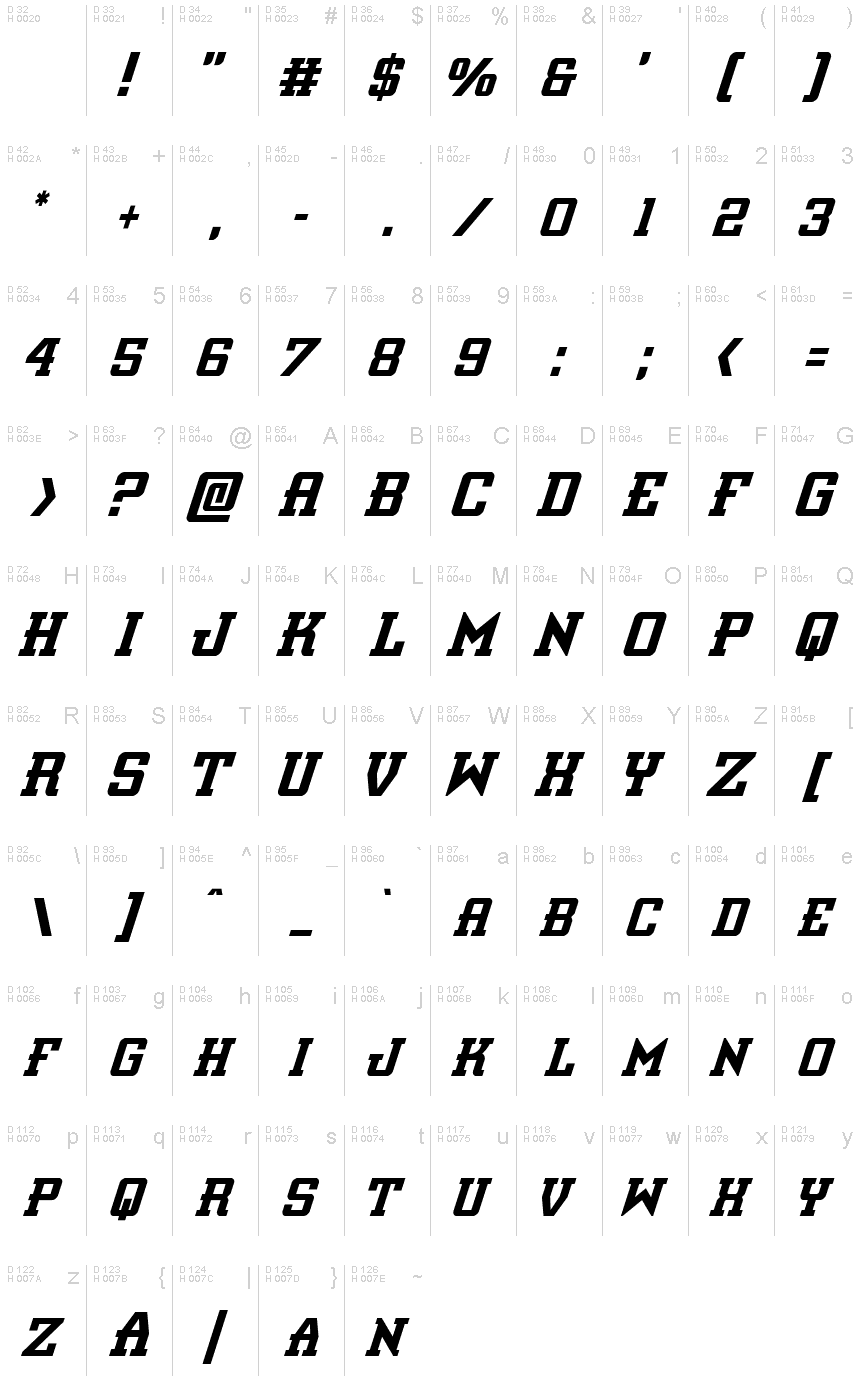
Interceptor Condensed Italic von Iconian Fonts ist eine kostenlose, futuristische Display-Schrift mit einem dynamischen, comicartigen Neigungswinkel. Die Buchstaben lehnen sich stark nach rechts; dank der abgeknickten Ecken, der blockartigen Stärke und der scharfen Keilschnitte wirkt das gesamte Design eher wie eine actionreiche Verfolgungsjagd als wie eine neutrale, moderne Schrift.
Sie passt perfekt zu Plakat-Überschriften, E-Sport-Branding, Spieletiteln, actiongeladenen Verpackungen und Cover-Texten – überall dort, wo eine kostenlose Schrift schon vor der Bildgestaltung für Bewegung sorgen muss. Nutzen Sie sie für kurze Wörter, Monogramme oder Logo-Namen, die geladen und mechanisch wirken sollen, denn die Großbuchstaben bringen diesen schwungvollen Vorwärtsdrang von Natur aus mit.